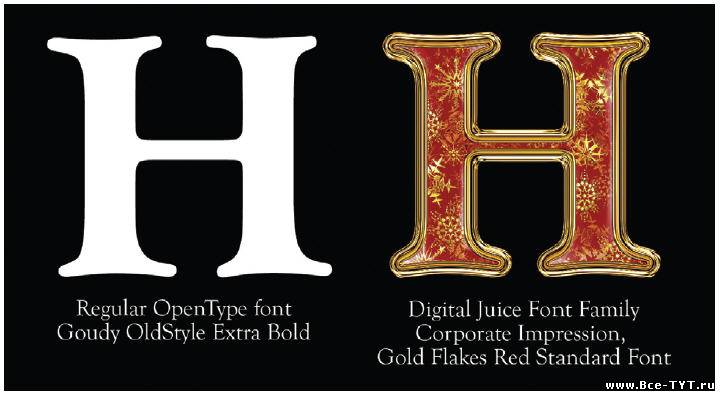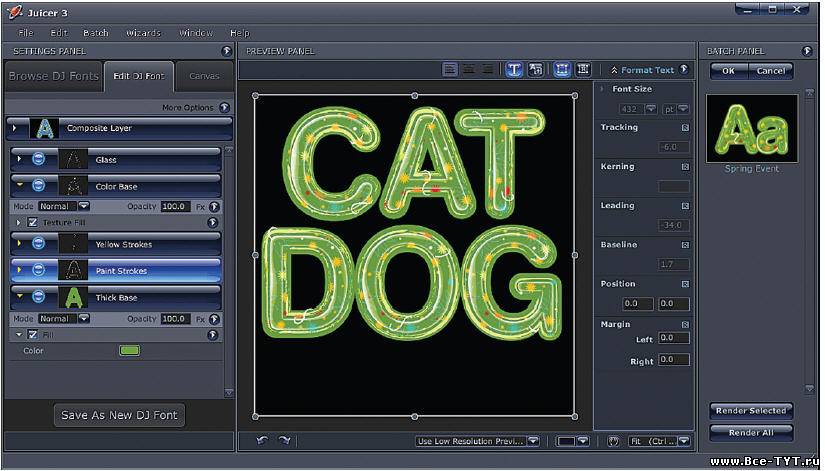
Большинство людей знакомы с основными шрифтами, поскольку они обычно предустановлены на компьютере и доступны в таких программах как Word или простой текстовый редактор. DJ Fonts это немного другое. Хотя в них включены стандартные OpenType шрифты для каждой группы DJ Font Family, сами по себе DJ Fonts не являются шрифтами в традиционном смысле. До них нельзя добраться инструментами выбора шрифта, предусмотренными в программном обеспечении как, например, в Word.
Простыми словами DJ Fonts – расположенные на слоях графические шрифты. Хотя их можно модифицировать как свойства любого текста (размер шрифта, кернинг и т.п.) в приложении Juicer, конечный результат будет графическим. Все шрифты легко редактируются, выводятся в различных форматах для импорта в другие графические программы.